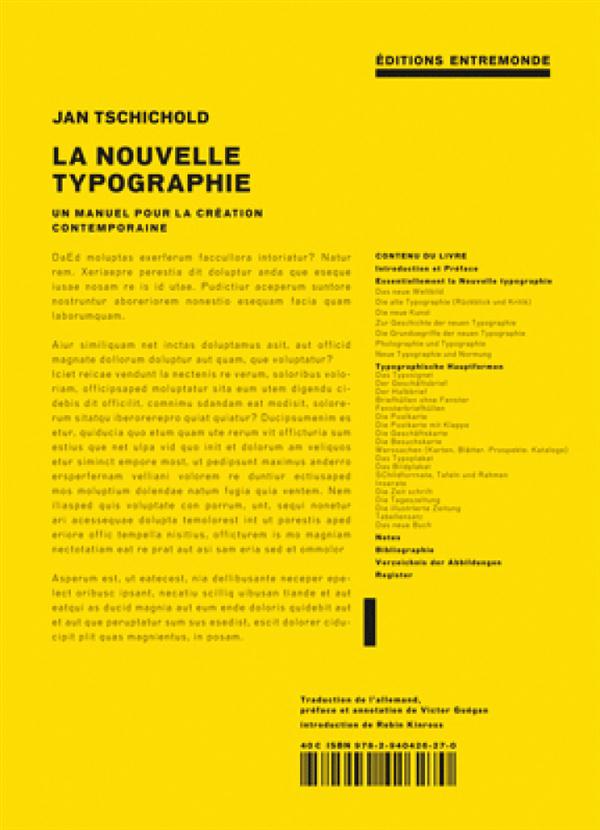
La nouvelle typographie. L'ouvrage emblématique de Tschichold, La Nouvelle Typographie (1928) est un véritable manifeste pour la modernité, analogue dans son domaine au livre du Corbusier Vers une architecture. Prenant la forme d'un manuel, l'auteur y fait table rase de la typographie ancienne qui ne trouve grâce à ses yeux que dans son contexte historique, maintenant dépassé. Pour concevoir son histoire de la typographie, Tschichold s'est d'abord tourné vers l'art moderne.
Pour lui, l'ancienne ère, centrée sur l'individu, a laissé place à une nouvelle époque, celle de la reproductibilité et de la dissolution de l'art dans l'architecture et autres formes directement publiques. La vie ainsi bouleversée, mécanisée, urbanisée, accélérée, le centre de gravité s'est déplacé vers le social et le collectif. Il s'agit d'en prendre acte. Les idées et le langage utilisés sont caractéristiques des textes modernistes de cette époque.
Cette révolution agit comme une lame de fond dans tous les domaines de la création, de la nouvelle architecture au théâtre politique de Bertolt Brecht, du mobilier tubulaire au cinéma de Dziga Vertov et jusqu'à la littérature. Les avant-gardes ; les futuristes, le mouvement Dada, le mouvement De Stijl, les constructivistes russes, le Bauhaus dessinent une véritable constellation internationale dont s'abreuvent les nouveaux typographes autant qu'ils y apportent leurs contributions.